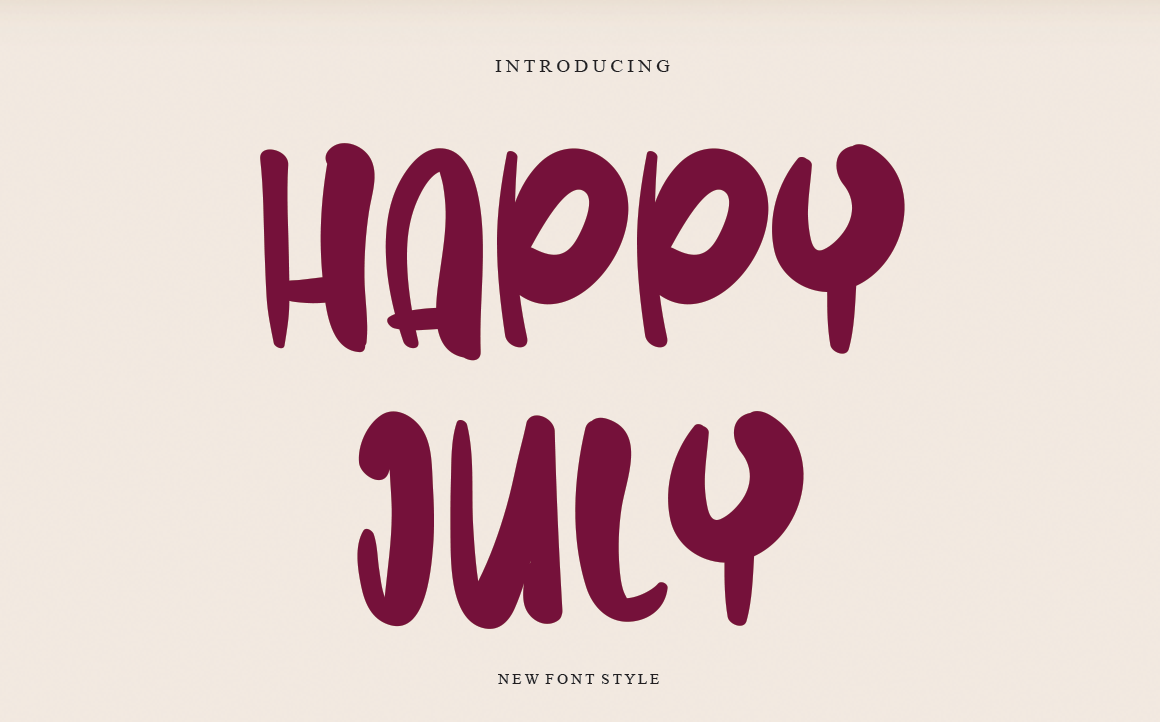
Happy July Display Font – Download Grátis
Esta ‘Happy July Display Font’ é uma escolha perfeita para quem busca algo que seja único, divertido e amigável ao mesmo tempo. Seja você criando conteúdo para Instagram ou desejando um toque elegante de calligrafia para projetos DIY, este font será a chave para transformar qualquer ideia em uma verdadeira obra de arte. É perfeito para quem adora fazer algo novo e divertido com letras digitais. Com certeza vai dar mais vida aos seus projetos de design gráfico!